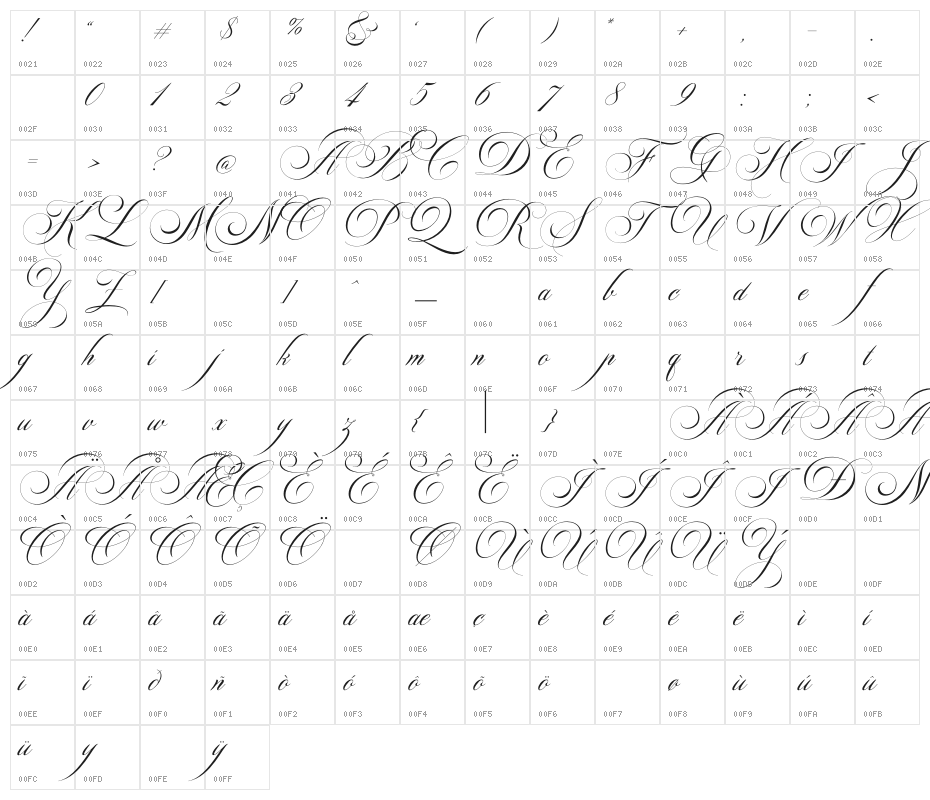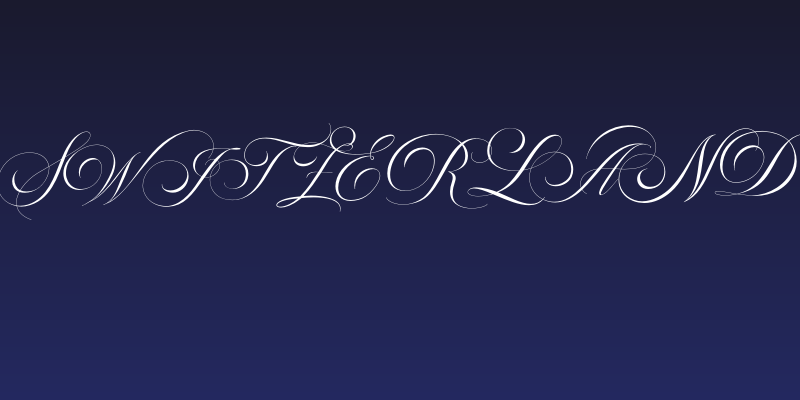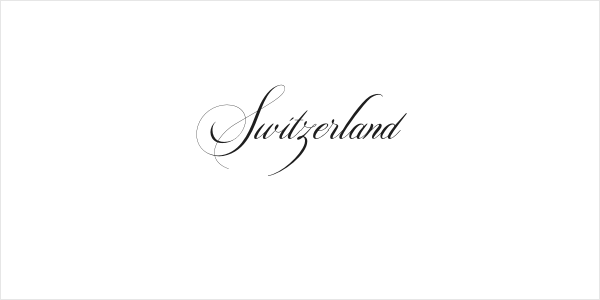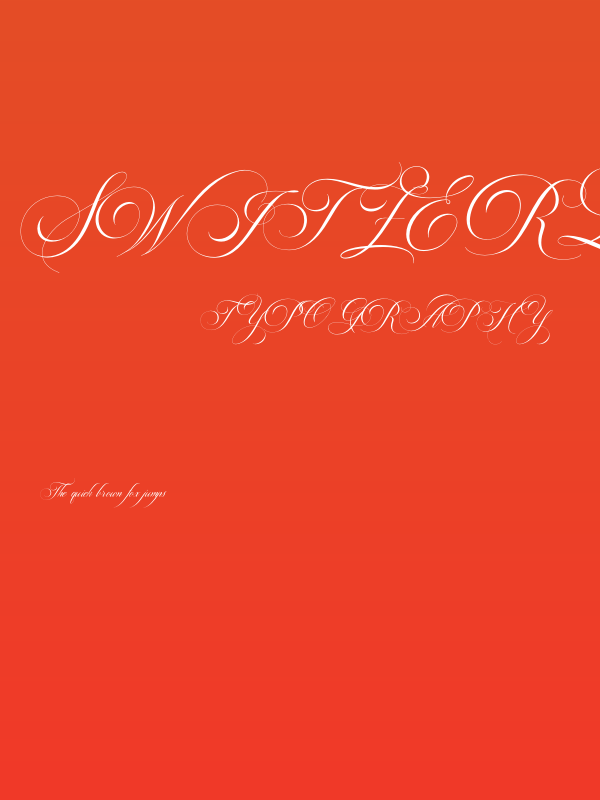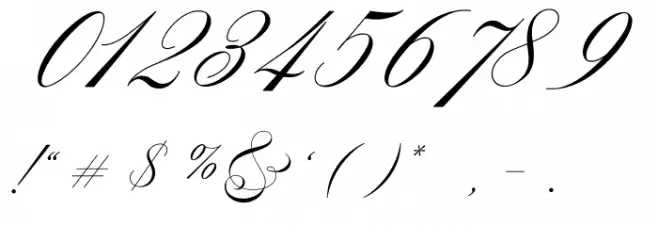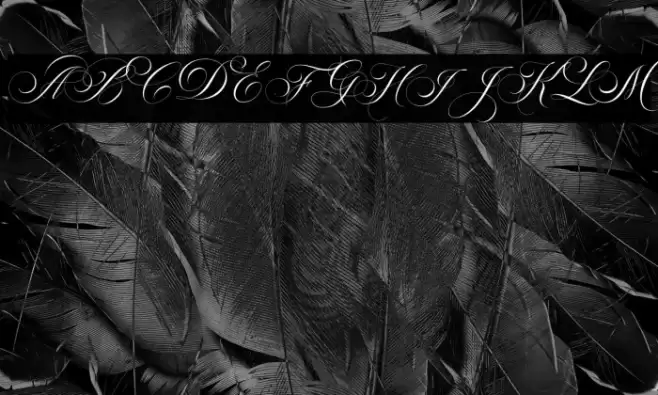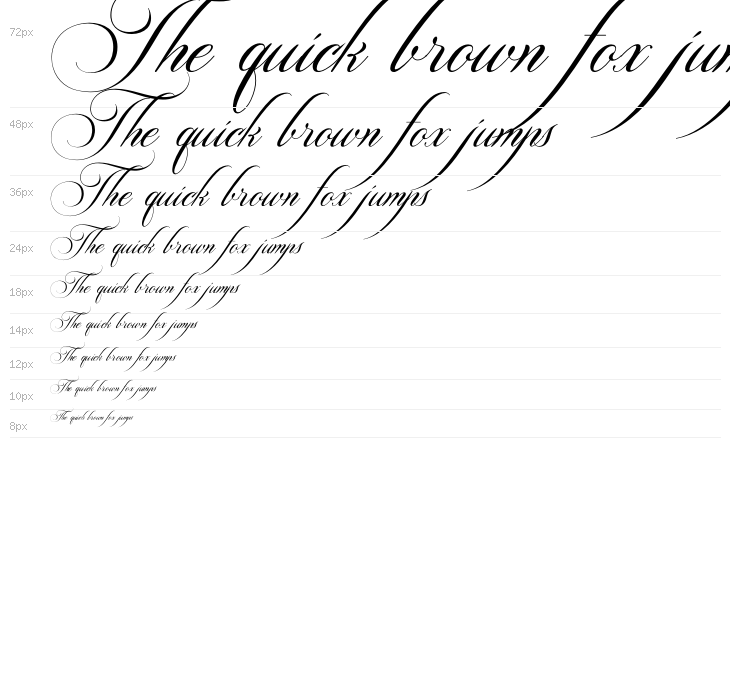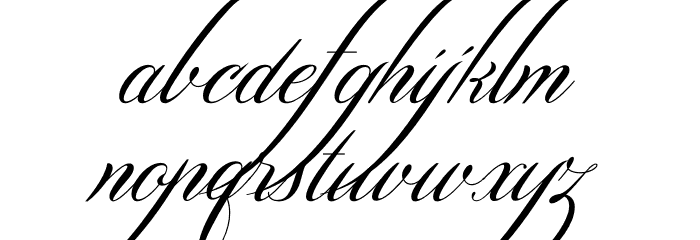
Switzerland Font
✎ Script
| श्रेणियाँ | Script |
| इटैलिक | Yes |
| कंट्रास्ट | High |
| समग्र शैली | Decorative |
| उपयोग का मामला | Headlines, Logos |
| सुझाए गए प्रोजेक्ट | Ideal for wedding invitations, luxury branding, greeting cards, and elegant signage. |